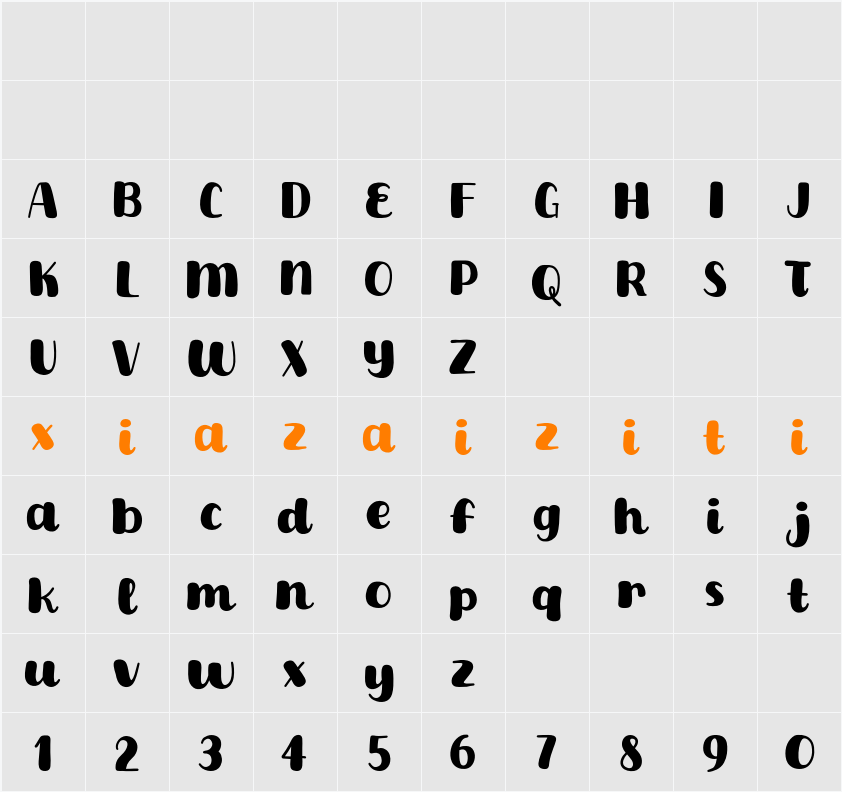
Xmas Show
Xmas Show,这款字体结构工整、笔画清晰,兼顾美观与易读性,适用于标题、正文、海报、包装、LOGO 等多种场景。字形优雅稳定,风格百搭耐看,适配日常排版与创意设计,让文字呈现更舒适、更具质感。Xmas Show一笔一画,皆是细节,以均衡的比例、流畅的线条打造舒适视觉体验,字形端正大气,风格简约现代。无论是商业设计、品牌宣传还是日常排版,都能轻松驾驭,让文字更有格调与力量。Xmas Show字体下载。
• 制造商: Khurasan
• 设计师: Khurasan